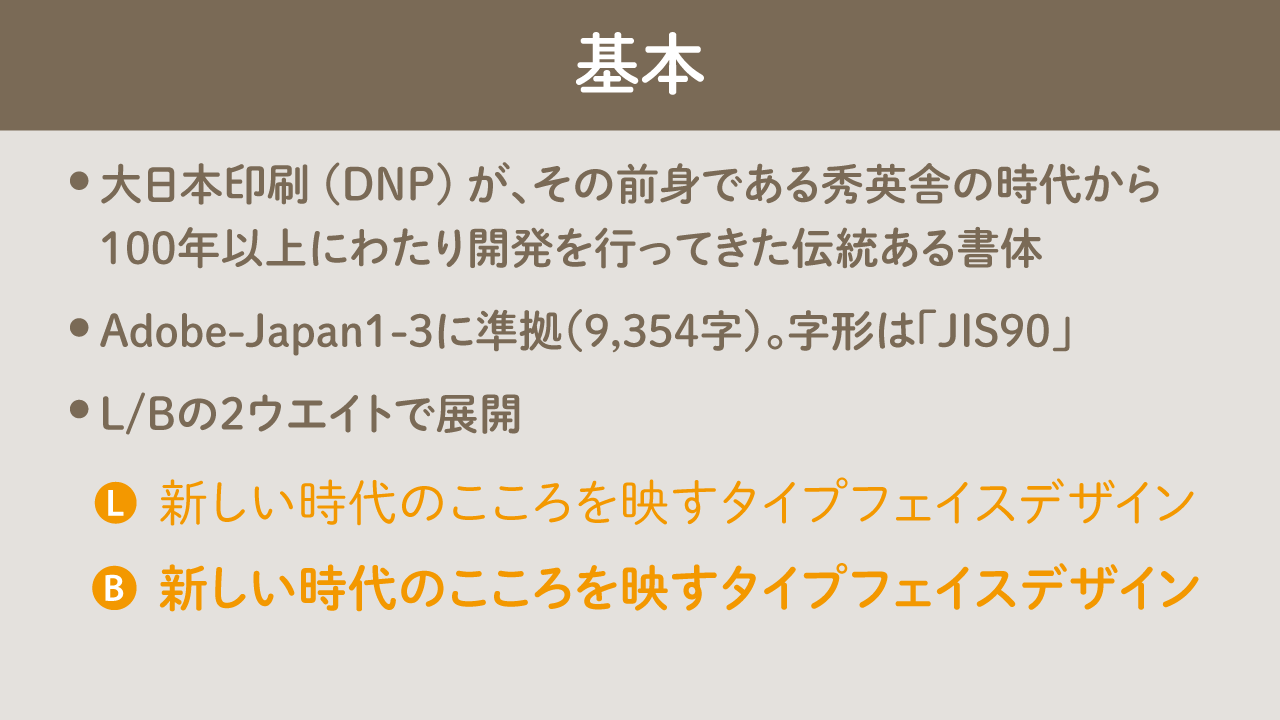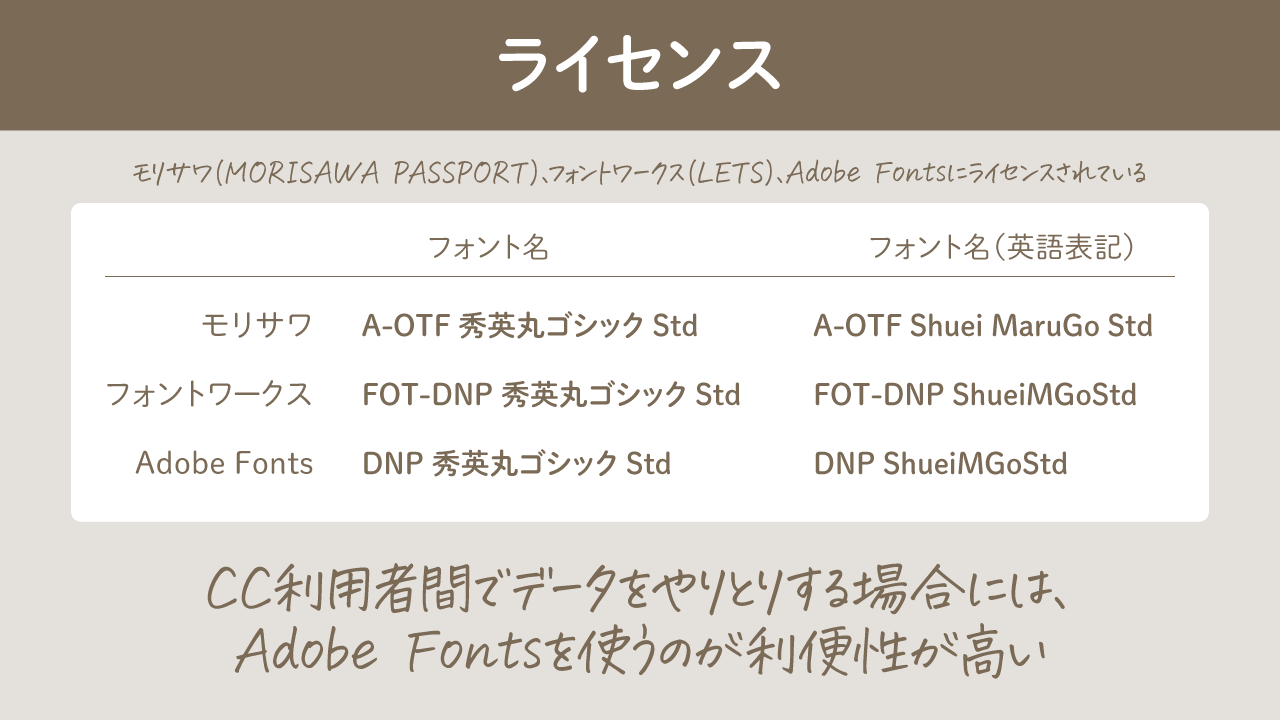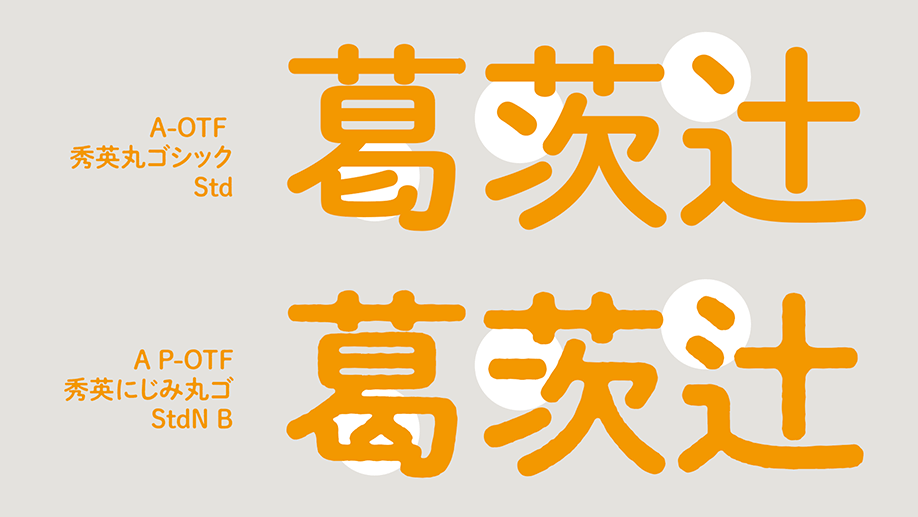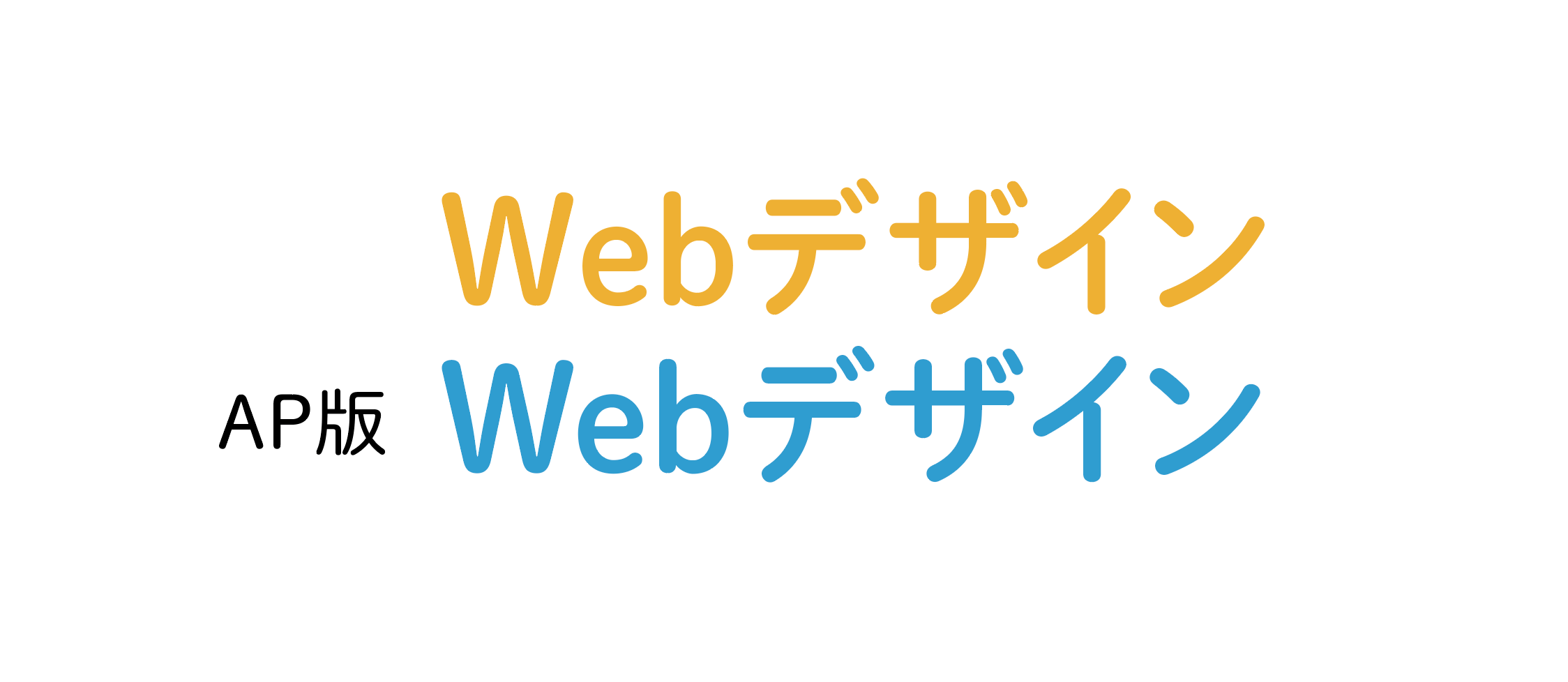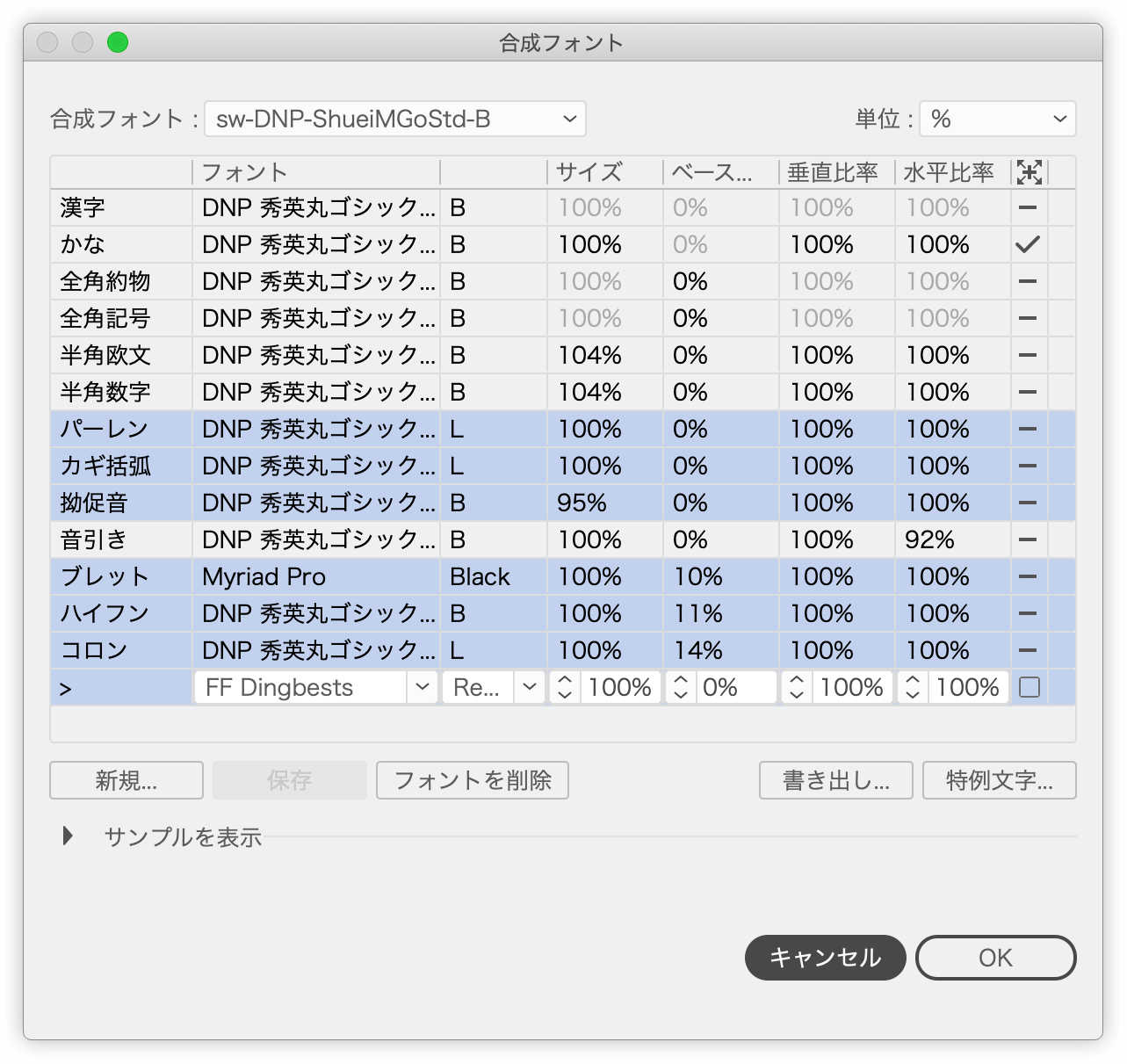
「秀英丸ゴシック」について
クラシックな印象を持ちつつも柔和で使いやすい人気書体「秀英丸ゴシック」についてまとめてみました。
ベーシック
- 大日本印刷(DNP)が、その前身である秀英舎の時代から100年以上にわたり開発を行ってきた伝統ある書体
- L/Bの2ウエイトで展開
- Adobe-Japan1-3に準拠(9,354字)。字形は「JIS90」
派生フォント
モリサワは、2018年から“にじみ”版(ウェイトは「B」のみ)、2020年からAP版(和文・欧文ペアカーニングと最新のIVSに対応した書体)を展開。
- AP版、「にじみ」バージョンもStdに準拠
- いずれもStd版(JIS90字形)、StdN版(JIS2004字形)が用意されている
- Nフォントを利用したい場合にはモリサワのAP版を選択
AP書体
モリサワの書体は、AP版にアップデートされつつあります。AP版の特徴は次のとおり。
- メニュー名を「A P-OTF〜」と表記して区別されている
- 令和合字を追加
- 和文・欧文ペアカーニングと最新のIVSに対応した書体
- アプリケーション上でペアカーニングの値を適用して使うことで、より美しい組版を実現
若干ですが、Wとeの間が詰まっています。
「A-OTF~」から始まるフォントと、「A P-OTF~」から始まるフォントは別書体の扱いとなり、互換性はありません。
合成フォント
私の場合、DNP 秀英丸ゴシック Stdを元にした合成フォントを作って運用しています。
カッコ類、ハイフン、コロン、小書きのかななどを調整しています。